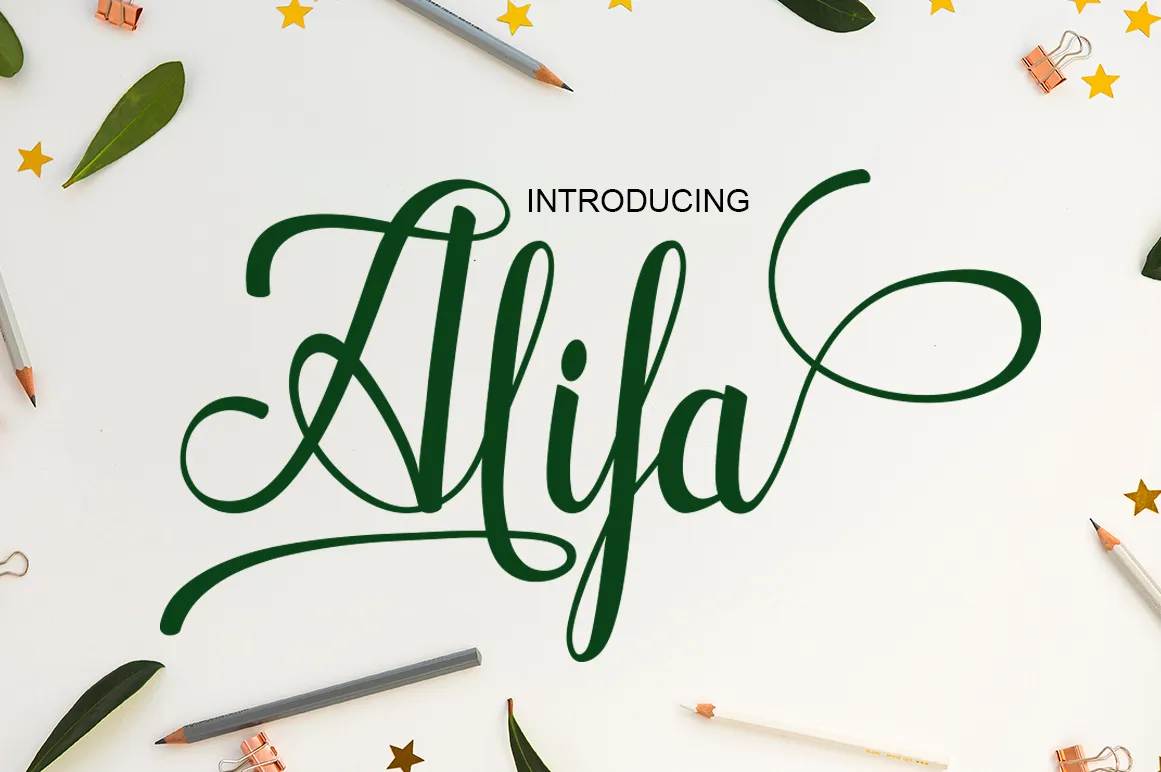
Alifa Script Font – Download Grátis
A fonte ‘Alifa Script Font’ é uma elegante combinação de estilo tradicional com a modernidade, criada pelo talentoso designer adymarwah52. Com um design inspirado na escrita clássica e elementos de arte decorativa, essa fonte oferece um toque pessoal e único para qualquer projeto. Repleta de personalidade e sofisticação, ‘Alifa Script Font’ é perfeita para criar uma aparição memorável. É ideal para uso em cartões de convite, anúncios ou até mesmo como material empresarial, garantindo um toque criativo e moderno. O designer adymarwah52 não apenas respeitou a tradição da escrita, mas também adicionou uma pitada de contemporaneidade com detalhes que chamam atenção. Seja em cartões de aniversário, materiais de marca ou até mesmo letras de propaganda, esta fonte é um ótimo recurso para aqueles buscando algo único e impressionante. Com ‘Alifa Script Font’, adymarwah52 criou uma opção única que combina com muitos estilos de design. Essa fonte não apenas traz um toque autêntico à qualquer projeto, mas também cria uma conexão entre o passado e o presente, oferecendo uma nova experiência visual para cada mensagem impressa.